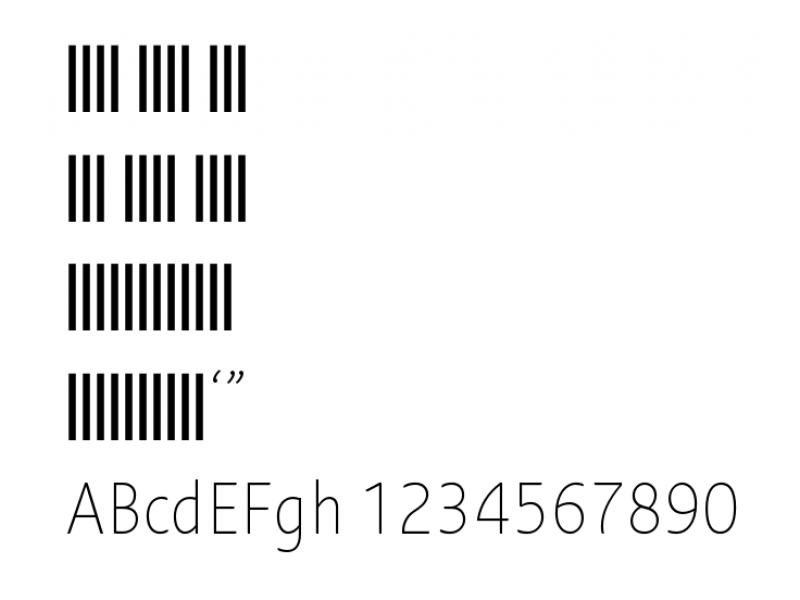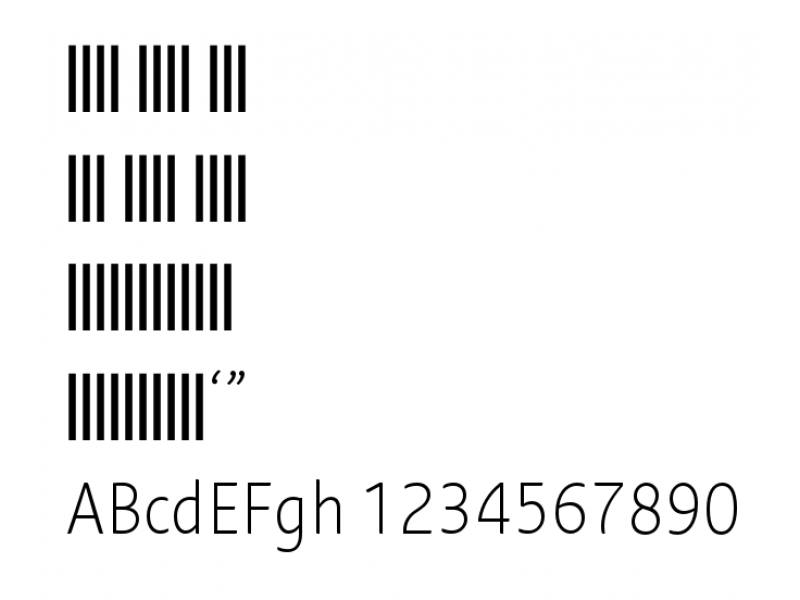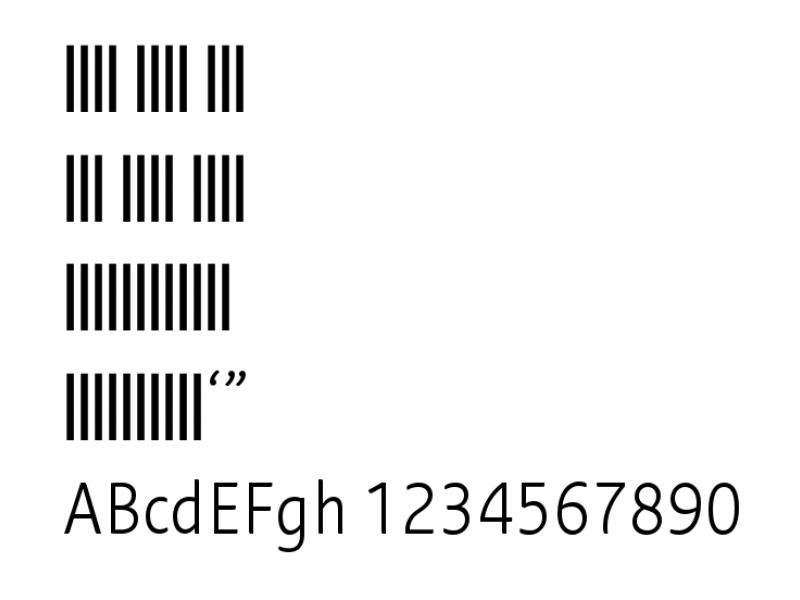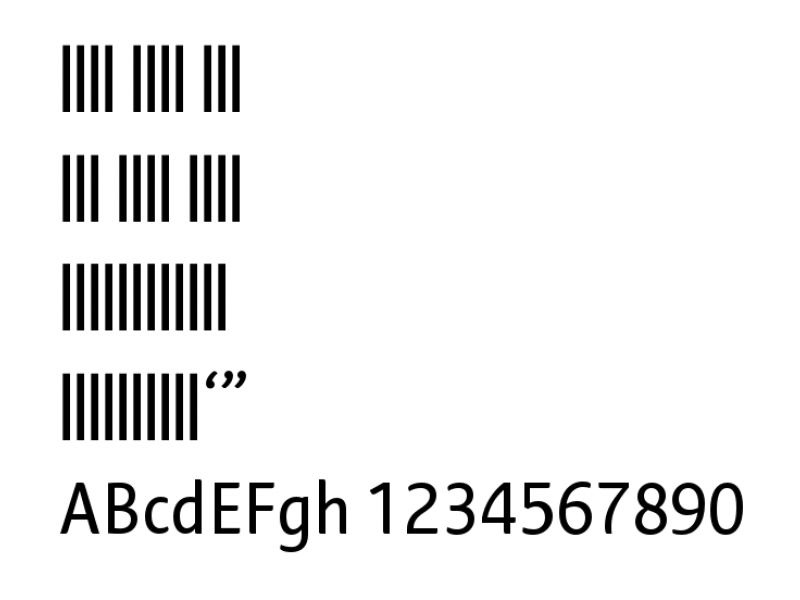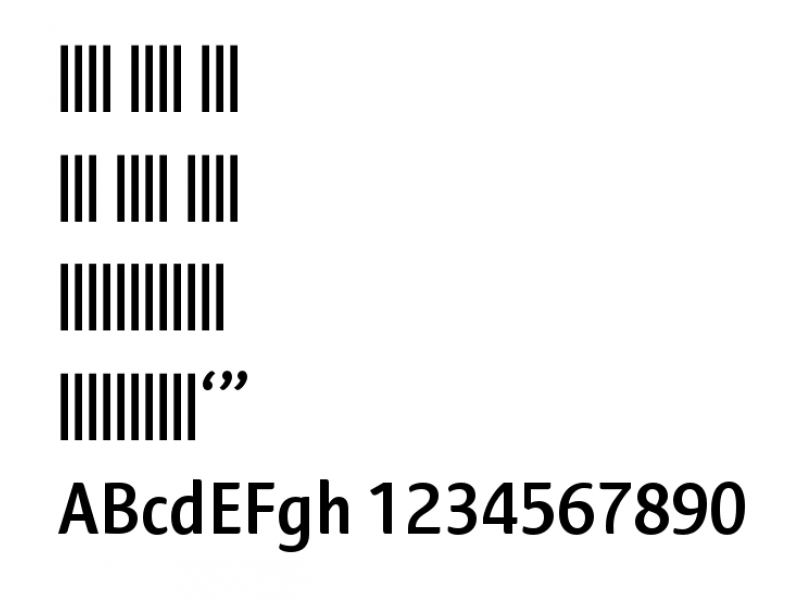
아리따 글꼴은 고딕계열의 트루타입(True Type) 글꼴이다. 홍익대학교 안상수 교수, 서울여자대학교 한재준 교수, 글꼴 디자이너 이용제 등이 제작하였고, 한글 1만1172자, 영어와 숫자 94자, KS코드 기준 특수문자 등을 포함하고 있다. > 아리따돋움, 아리따부리(2014년 추가), Arita Sans(2012년 추가, 영문글꼴)로 3가지로 구성되어 있다. thin-light-medium-semibold-bold의 5가지의 굵기를 제공한다.
2006년 한글날을 기념하여 아모레퍼시픽이 개인 및 기업 사용자에게 무료로 공개했으며 2012년에는 네덜란드의 대표적 디자인 그룹인 스튜디오 둠바의 크리에이티브 디렉터를 역임한 미셸 드 보어(Michel de Boer)에게 영문글꼴 디자인을 의뢰하여 개정한 3.0버전을 발표하였다. 지적재산권은 아모레퍼시픽에 있다.
2012년 선보인 아리따 글꼴의 첫 로마자 서체다. 아리따 산스는 휴머니스트 산 세리프 계열로 부드럽고 우아한 표정을 지니고 있다.